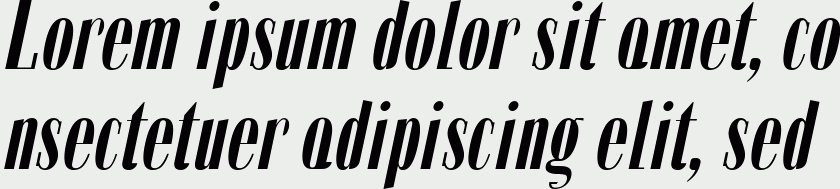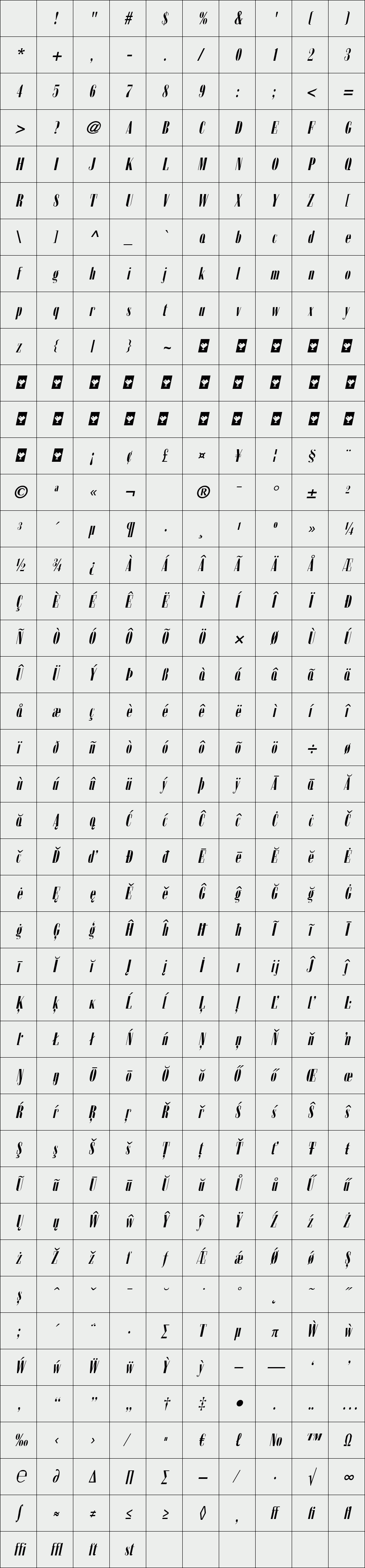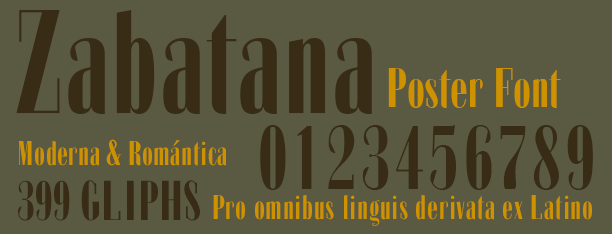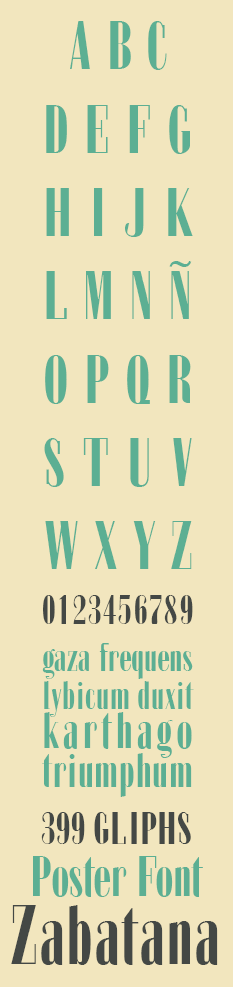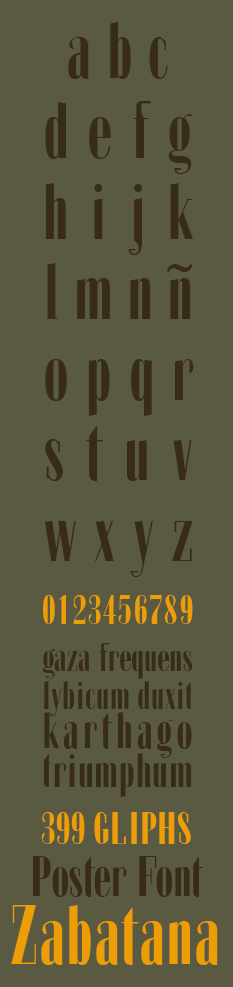
Zabatana
/ Zabatana Poster Italic
Fuente comprimida de estilo modernista y romántico y sin serif, inspirada en tipografías decorativas de los principios del S.XX.
El diseño de la fuente está realizado para usarla en tamaños por encima de los 24pt, es una tipografía de proporciones heavy y comprimida, y su utilización óptima en diseño gráfico viene dada para el uso en carteles, poster, afiches y grandes rótulos, es una poster font, también sirve perfectamente para títulares en diseño editorial, maquetación de publicaciones, etc.